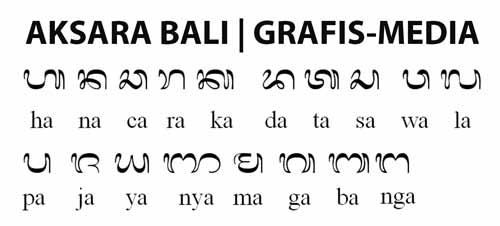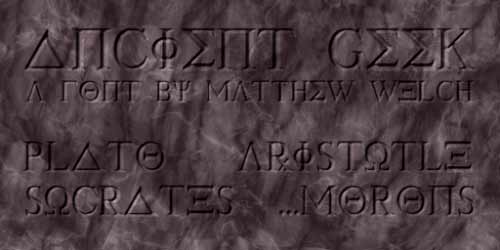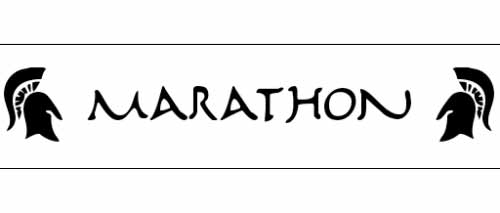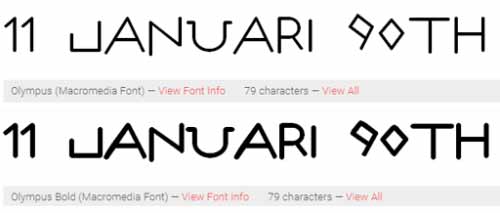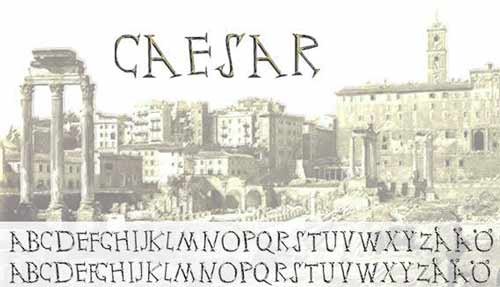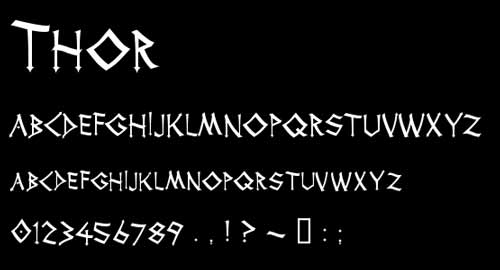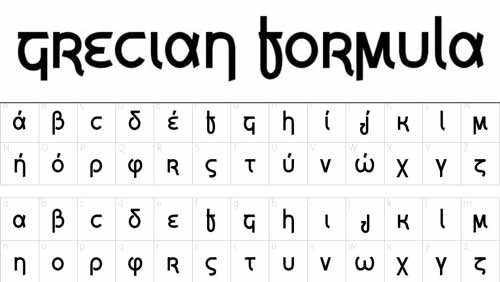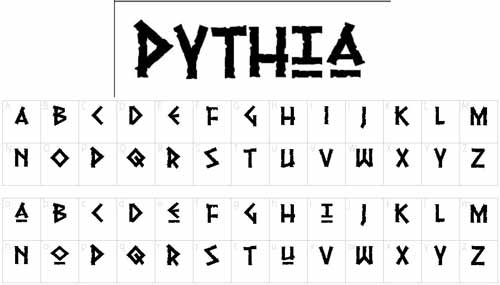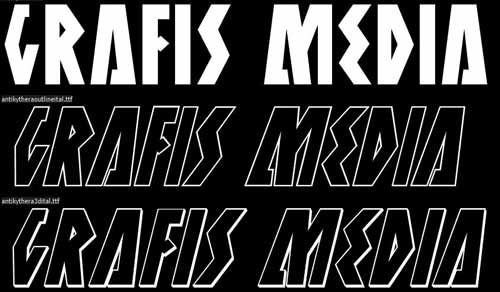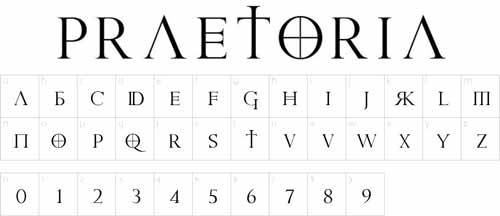
20 Font Kuno Jaman Dulu dan Font Aksara Jawa, Bugis, Bali Untuk Desain Grafis
Aksara adalah sistem simbol visual yang tertulis pada media berupa kertas, batu, kain, kayu dsb, untuk mengungkapkan unsur-unsur tertentu dalam suatu bahasa. aksara juga dapat disebut sebagai sistem tulisan. sedangkan Abjad dan alfabet berbeda lagi,karena merupakan tipe berdsarkan fungsinya.
Di Indonesia ada beberapa aksara yang terkenal dan memang sudah digunakan sejam jaman dahulu. bagi sobat yang mau mengetik atau menulis di komputer, bisa menggunakan font aksara dibawah, agar ketika di print out hasilnya bisa maksimal.
1. Font Hanacaraka | Aksara Jawa
Aksara jawa juga disebut dengan Hanacarakan dan carakan. salah satu sistem tulisan di Nusantara yang digunakan untuk menulis bahasa jawa serta bahasa lainnya, seperti sunda  dan bahasa sasak.
susunana aksara jawa
2. Font Aksara Bali
Aksara bali sangat erat hubungannya dengan jawa. lihat saja dari bentuk dan sebutannya.
contoh gambar aksara bali
3. Font Aksara Bugis  | OgieCappo Campotype
Lontara adalah nama aksara tradisional bagi suku Bugis – Makassar, yang digunakan sejak abad 17 hingga sekarang. lontara merupakan perkembangan dari tulisan Kawi yang digunakan di kepulauan Indonesia sekitar tahun 800-an, kemudia secara bertahap menjadi aksara bugis. (https://id.wikipedia.org/wiki/Aksara_Lontara)
gambar susunan aksara bugis | lontara bugis
Selanjutnya adalah font kuno yang biasa dipakai pada kerajaan maupun kekaisaran di dunia. misalnya pada kekasiran romawi, yunani, mesir, rusia dan lain-lain.
Tidak seperti aksara diatas yang memiliki bentuk berbeda dari huruf abjad pada yang biasa kita pakai sehari-hari. kalau font kuno dibawah ini, hanya gayanya saja yang diberikan nuansa kuno. tapi bentuk hurufnya tetap bisa dibaca seperti biasa. yaitu seperti huruf romawi.
1. Font Romawi Kuno | Heorot
Ffont heorot dengan bentuknya yang siku. tidak ada sedikitpun unsur lengkungan halus pada hurufnya. kalau mau dipakai, sangat cocok dengan desain tema kerajaan romawi.
2. Yunani Kuno |  Ancient Greek
Font yunani kuno ini pasti sudah sering kita lihat, apalagi di film-film hollywood tentang kerajaan.
3. Font Marathon
4. Font Olympus
5. Font Ceasar
Font ceasae terinspirasi dari reruntuhan bangunan pada masa kerajaan romawi kuno.
6. Font Diogenes
7. Font Gelio
8. Font Achilles
9. Font Thor
10. Font Pythia
Kalau font pythia lebih ke zaman batu. lebih kuno dari pada yang diatasnya. soalnya pada bentuk hurufnya seperti batu retak dan rusak. pasti kalau dipadukan dengan desain bertemakan alam sangat cocok.
11. Font Greecian Formula
12. Font Pompeji
13. Font Capitalis Goreanis
14. Font Antikythera
15. Font Alfabetix
16. Font Praetoria
17. Font Daily Routine
18. Font Dyonisius
19. Font Vengefulgods